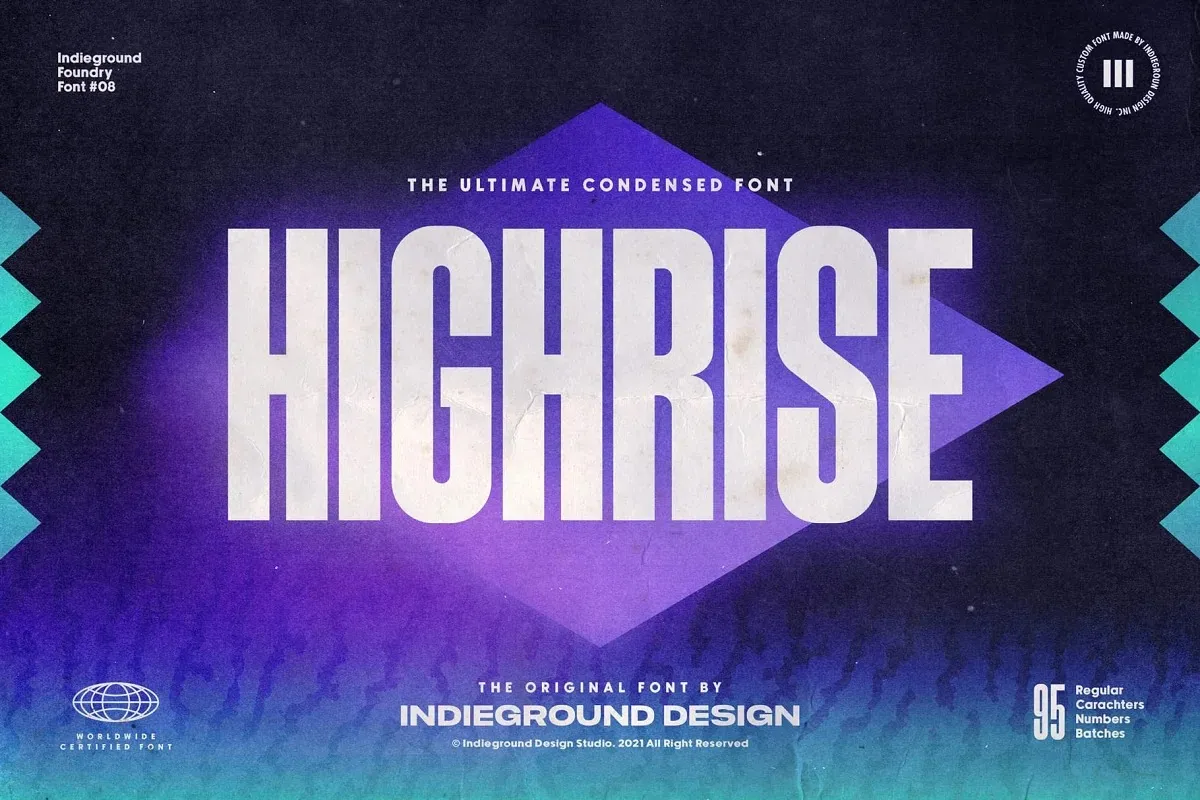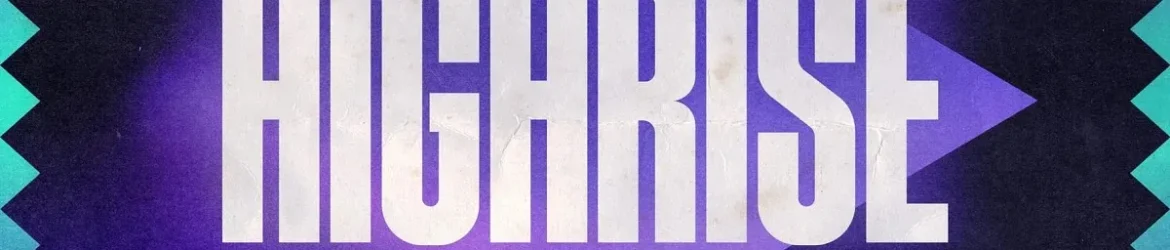
Esta font é uma extensão personalizada que traz tanto agressividade quanto simplicidade. Ela foi criada pelo designer de fontes Indieground Design Inc., adaptando-se a todos os projetos de design gráfico ou tipográfico. Esta font tem um clima minimalista, mas oferece uma aparência cool e peso para todos os seus trabalhos artísticos. A versão comercial regular desta font inclui três pesos condensados completos dos caracteres mostrados no preview. Se você está procurando por uma fonte que dê um toque moderno a todas as suas criações, este é o candidato perfeito.